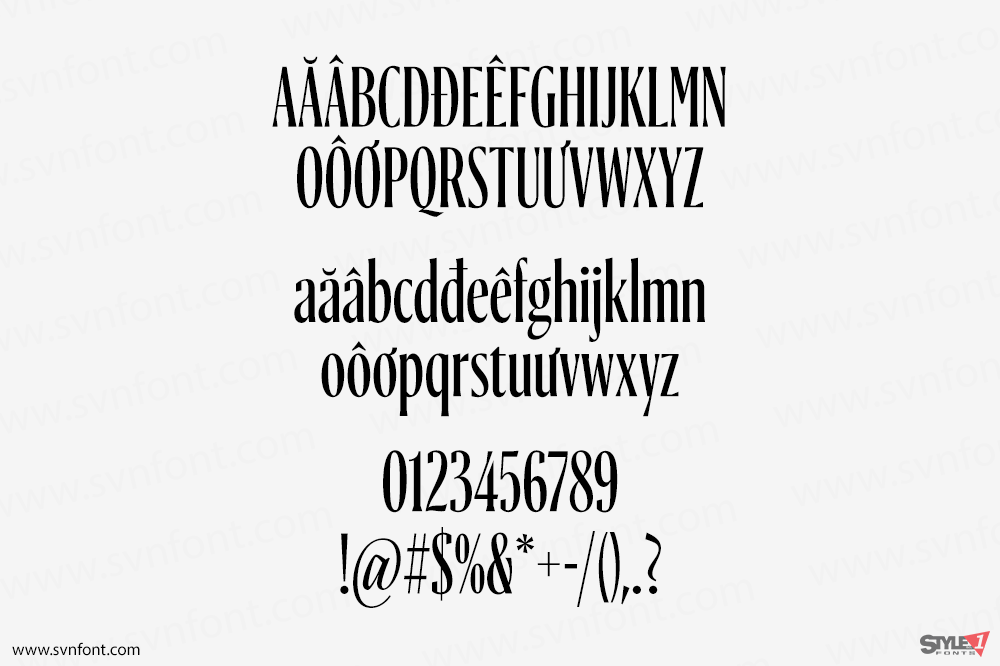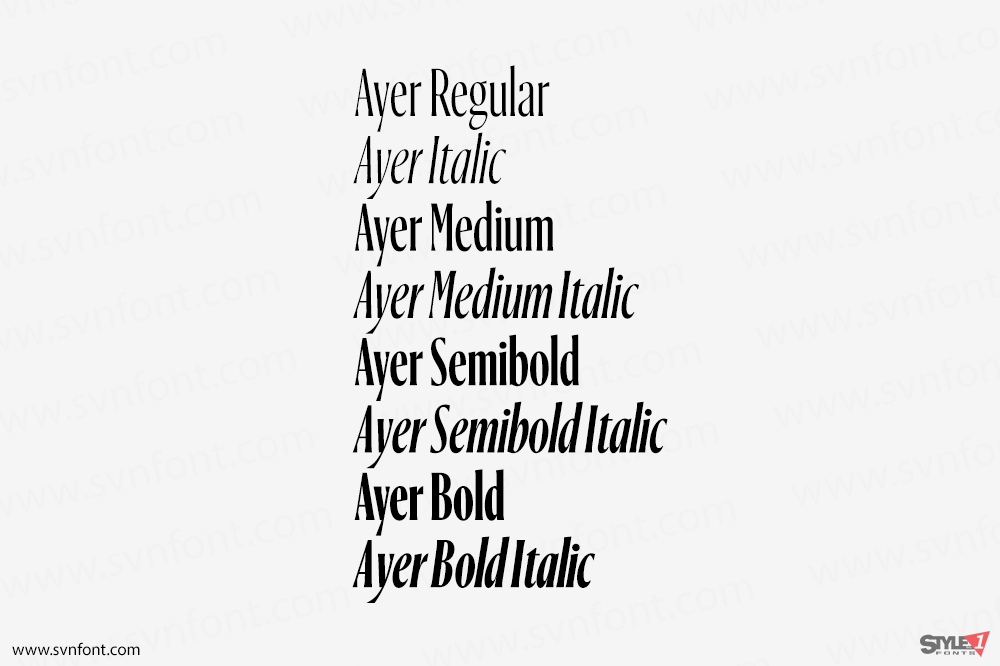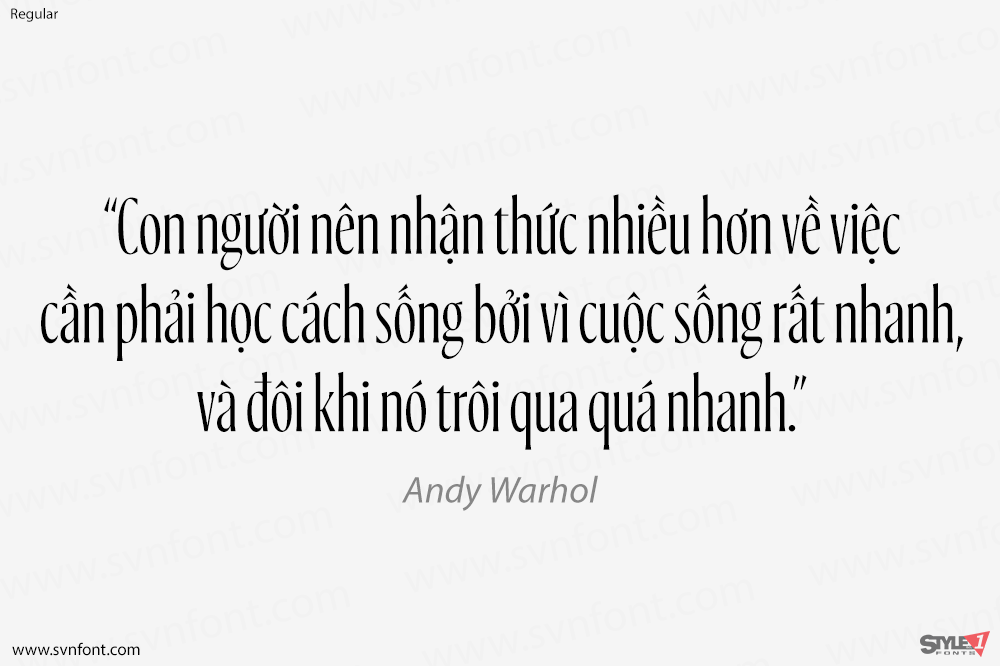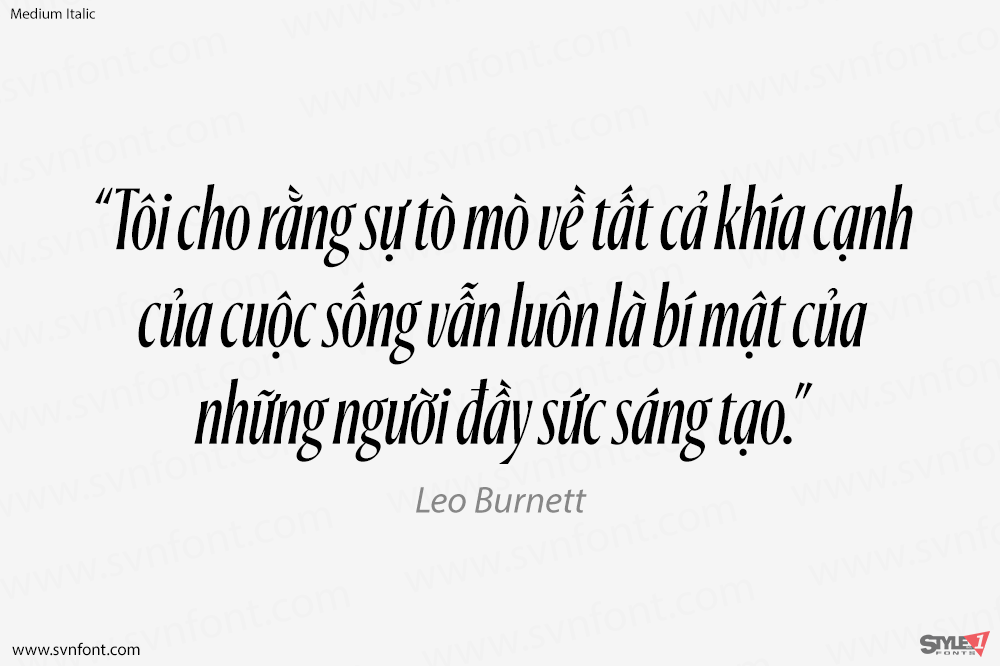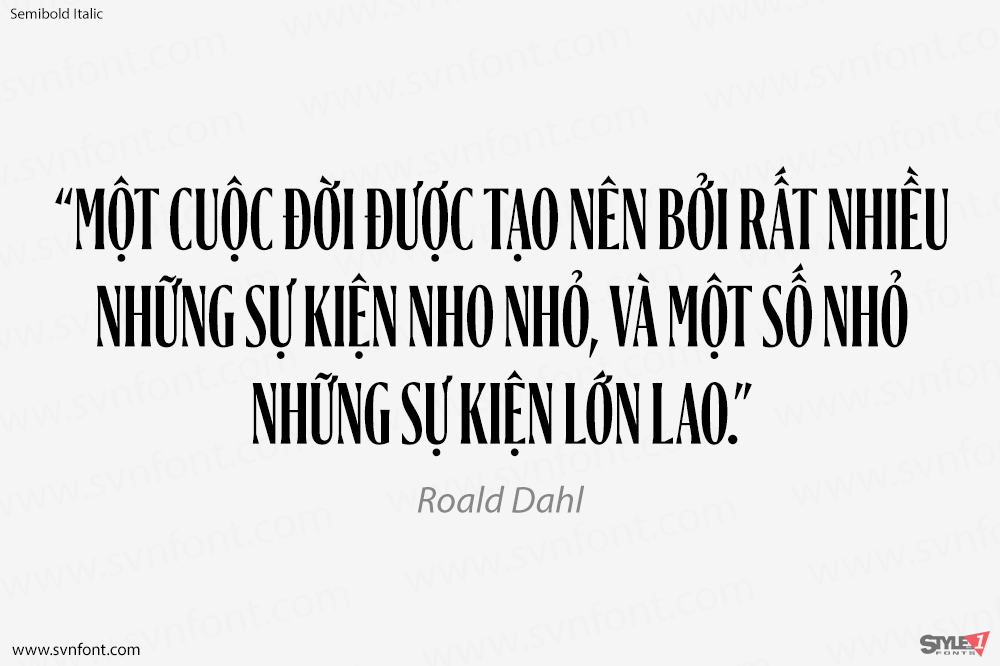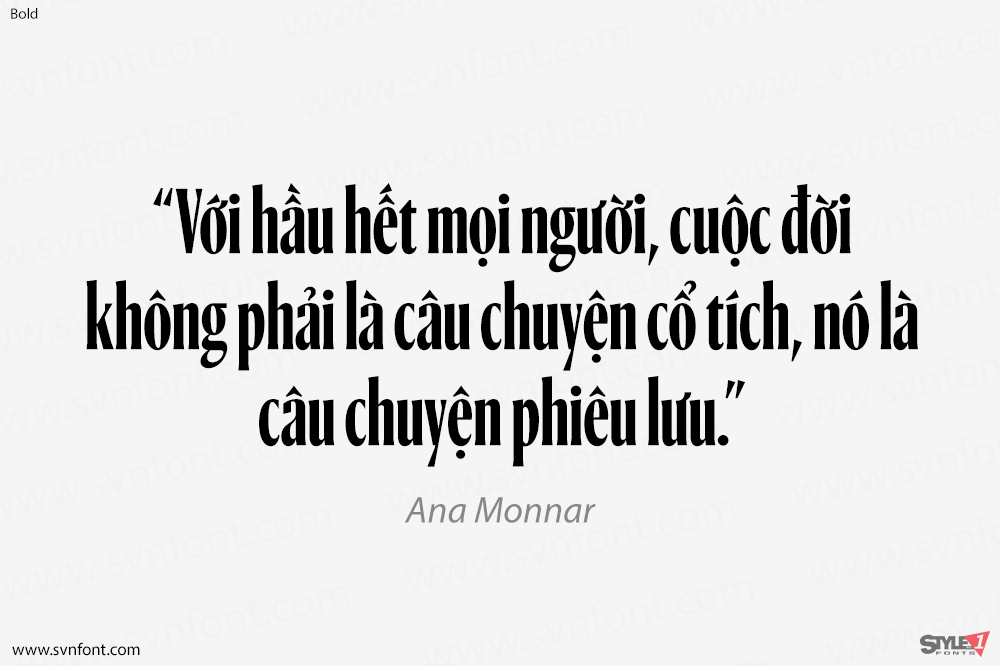
Ayer là một kiểu chữ display cô đọng, thanh lịch được thiết kế bởi Miguel Reyes từ năm 2016 đến 2019 cho tạp chí thời trang khổ lớn W. Giám đốc sáng tạo, Cian Browne, và giám đốc nghệ thuật, Jeffrey Burch, cần một kiểu chữ dễ biến đổi, có khả năng thể hiện cá tính mạnh mẽ ở nhiều kích cỡ khác nhau, ngay cả chỉ với vài ký tự. Ayer có độ tương phản cao hơn, và có thể được sử dụng từ 60pt trở lên hoặc để làm nổi bật tiêu đề trên nền tối.
Nhà thiết kế: Miguel Reyes
Nhà phát hành: Commercial Type